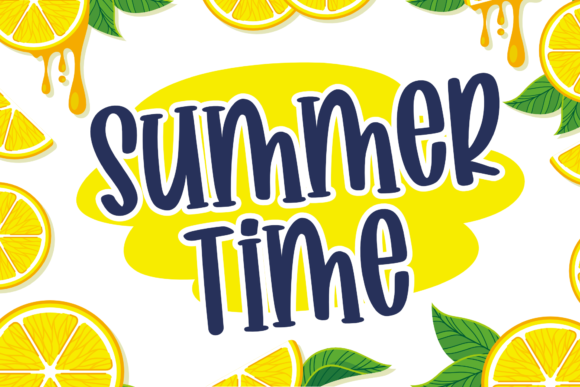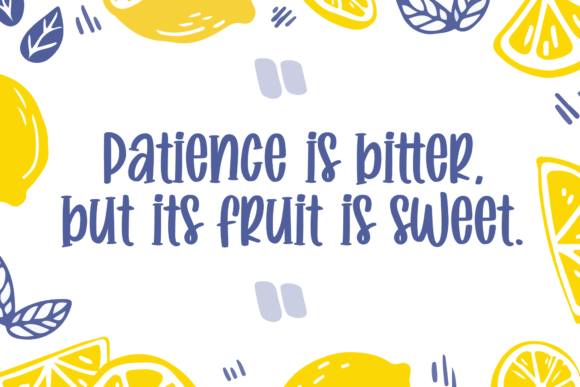
今天 Creative Fabrica 的限時免費字體是 Lemon Dreams,原價 $15 美元,現在限時 24 小時免費下載,還附帶商業授權。字體屬於可愛手寫字體,字形帶有俏皮的彈跳感!
字型介紹
Lemon Dreams 是由設計工作室 Holydie Studio 出品的手寫風格字體,自 2020 年上架以來累積超過 2856 次收藏,用戶評分也達到滿分 5.0 (共 10 則評價)。風格上帶點彈跳感、可愛。